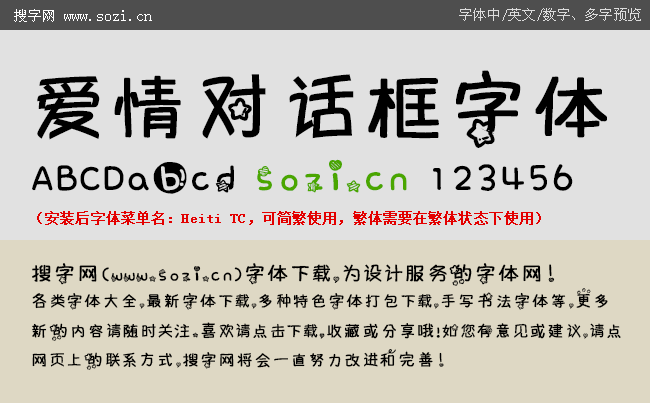
愛情對(duì)話框字體
搜字網(wǎng)給大家提供一款很卡通的手機(jī)中文字體下載。修改者給這款字體叫愛情對(duì)話框字體,這款手機(jī)中文字體以POP字體為原形,在筆畫間嵌入星星等卡通圖形,該中文字體趣味性強(qiáng),又保持了文字的識(shí)別度,非常適合喜歡卡通的朋友在手機(jī)上安裝使用。